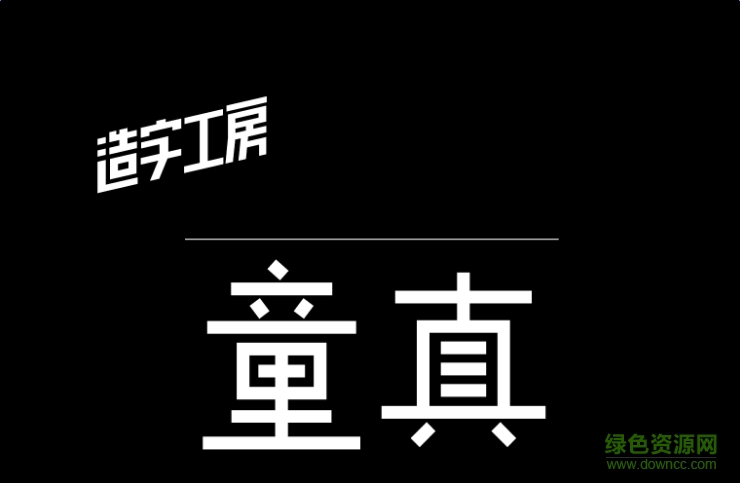
造字工房童真體是一款造字工房類可愛童趣風格字體軟件,童真體整體效果無拘無束,非常的滑稽,在兒童讀物設(shè)計方面有著不錯的應(yīng)用,歡迎到綠色資源網(wǎng)下載體驗,還有更多好看字體盡情期待!
造字工房童真體橫豎筆畫粗細較為統(tǒng)一,筆畫纖細,娟秀可愛,粗細勻稱,結(jié)構(gòu)輕巧,特點明確,起落筆及拐角直角設(shè)計,撇捺無多余贅點,整體風格簡單明了。適用于兒童讀物、報刊雜志標題、廣告設(shè)計、個性招牌等視覺環(huán)境,有著極強的應(yīng)用空間。